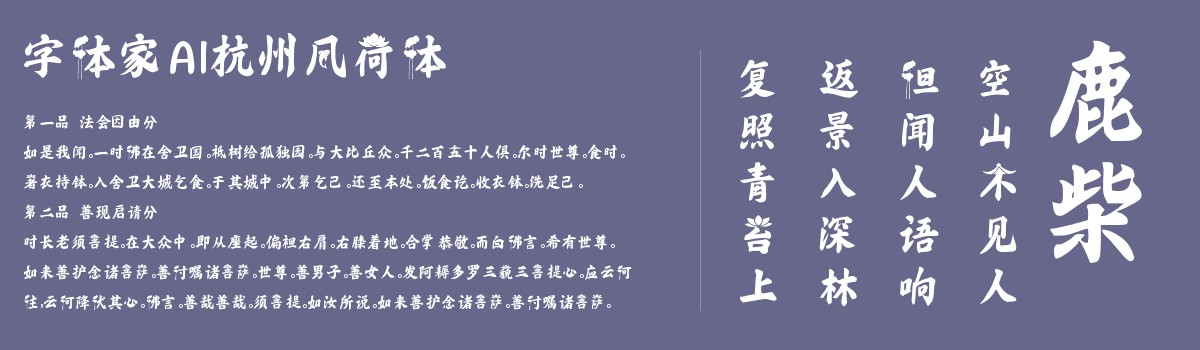
字体家AI杭州风荷体
每个城市都有它的独特魅力,而杭州的魅力,似乎藏在那一池荷叶、一缕酒香之间。字体家AI杭州风荷体正是捕捉了这份独特的杭州韵味。灵感源自西湖十景之一的曲院风荷,这款字体将历史与诗意融入到每一个字符中。设计师将“亻”巧妙地变成荷叶形状,“艹”犹如一朵盛开的荷花,横笔画则带着苏堤旁的浪漫情怀,仿佛诉说古时的雅致。无论是古风包装、手绘海报,还是漫画设计,杭州风荷体都能为作品增添文化底蕴。在现代与传统的交汇中,这款字体不仅是一种视觉享受,更是杭州风情的一次如梦旅程。